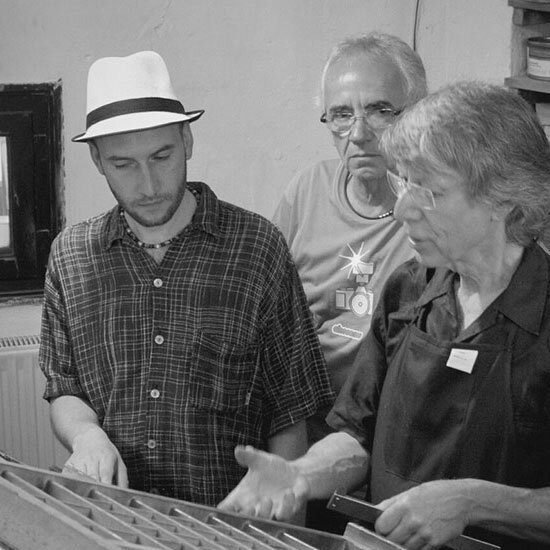
Elementare Typografie (12. bis 13. September 2015)
Bauhaus-Künstler Laszlo Moholy-Nagy erwähnt den Begriff der Neuen Typografie erstmals im Jahr 1923 in einem Beitrag zur Bauhaus-Ausstellung in Weimar. Jan Tschichold greift die radikalen Thesen der Bauhaus-Künstler auf und verbreitet sie im Laufe der 1920er-Jahre unter dem Begriff der Elementaren Typografie. In Weimar, dem Gründungsort des Bauhaus, beschäftigen wir uns im Rahmen des 2. Walbaum-Wochenendes in Theorie und Praxis mit dieser Stilentwicklung des Grafikdesigns und der Typografie.